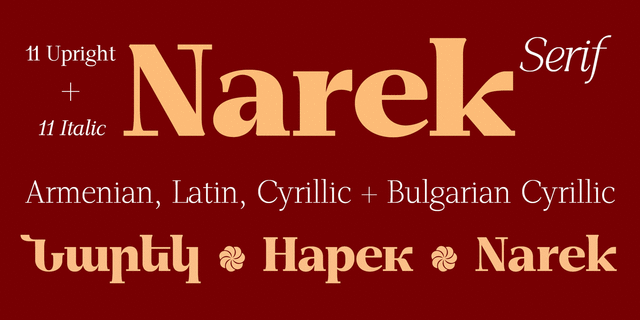
GHEA Narek Serif – это многофункциональная антиква с высоким контрастом. Гарнитура содержит начертания для текстового и акцидентного применения, поддерживает латиницу, кириллицу, в том числе ее болгарский вариант, и армяницу. Шрифт разработал Эдик Габузян в 2014 году.
Ассоциации c начертанием GHEA Narek Serif Extra LightКачества и характер:
тонкий, легкий, деликатный, ровный, гармоничный, техничный, современный, статичный, культурный, образованный, устойчивый, серьезный, твердый, четкий, резкий, острый, роскошный, гламурный, модный, ювелирный, художественный